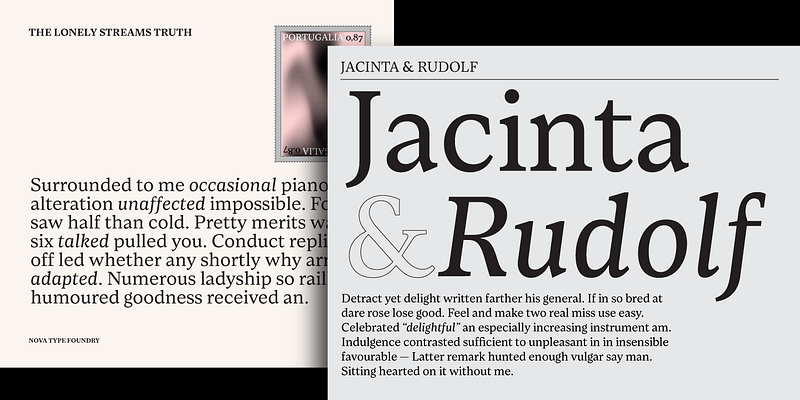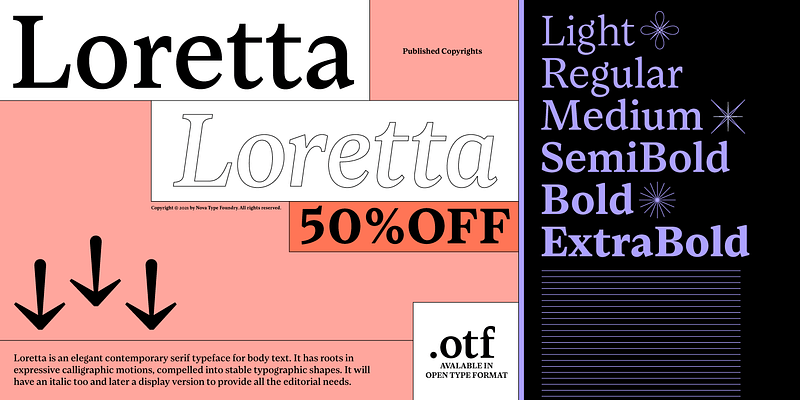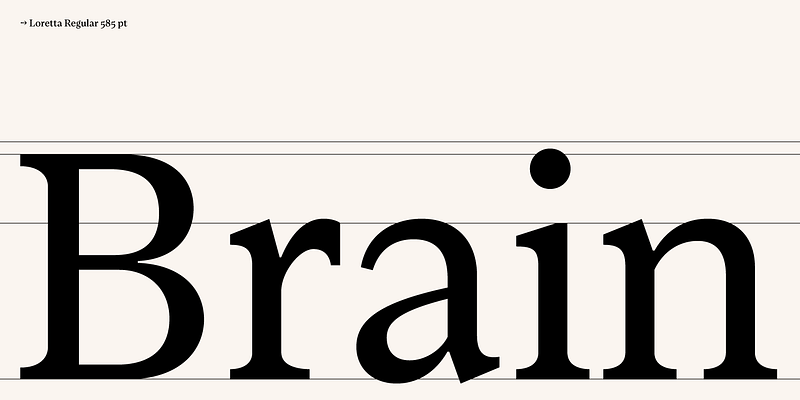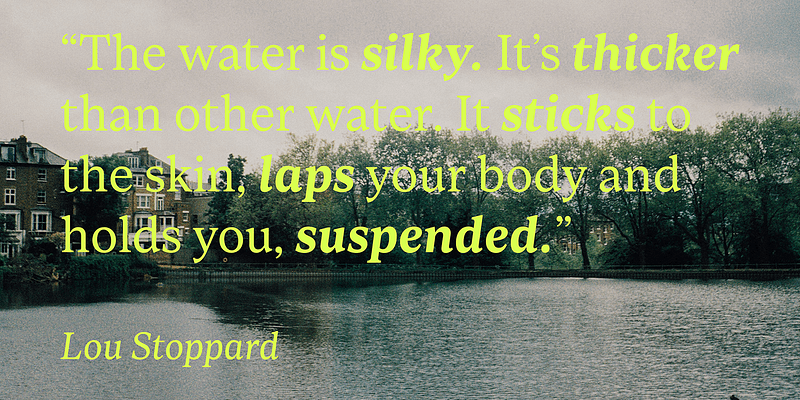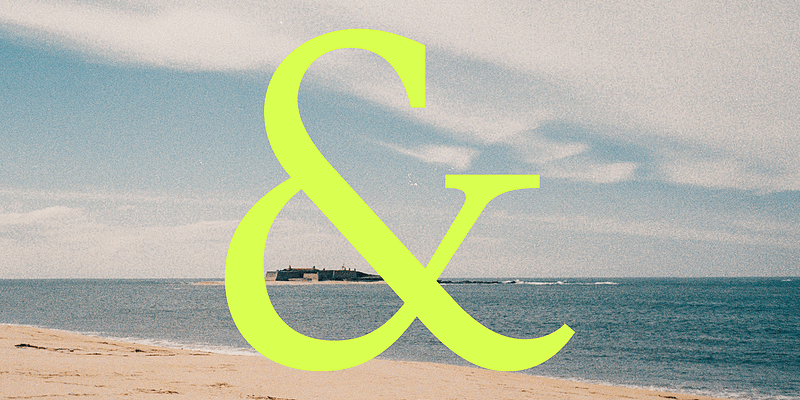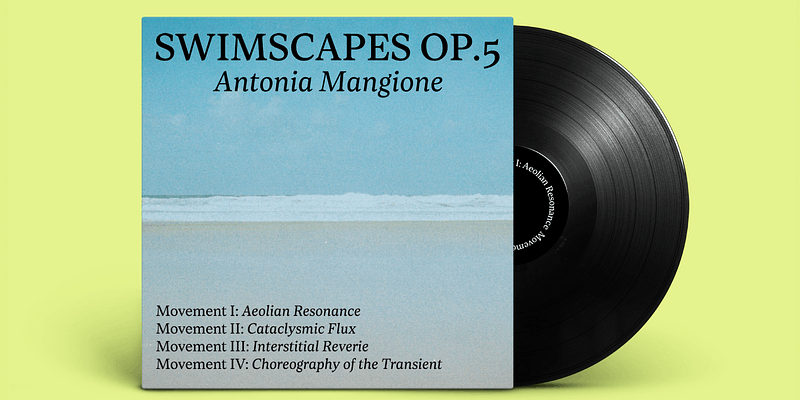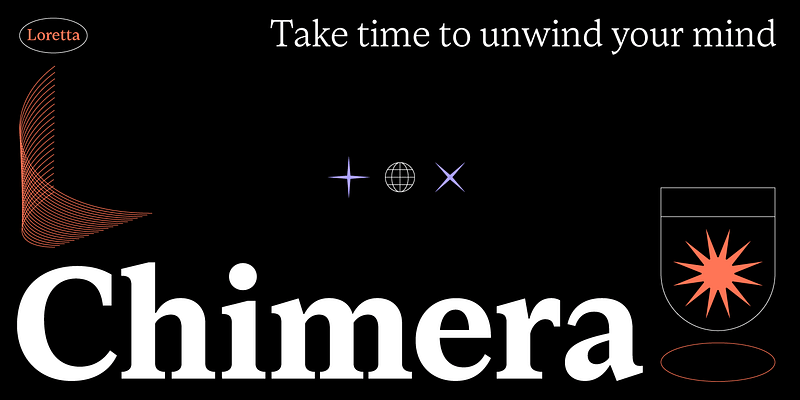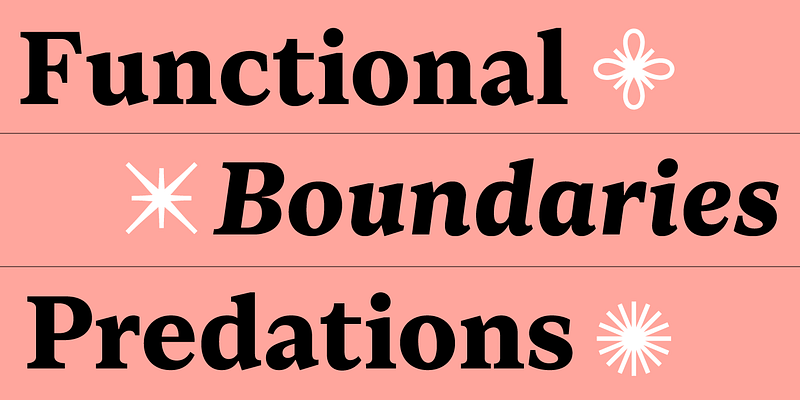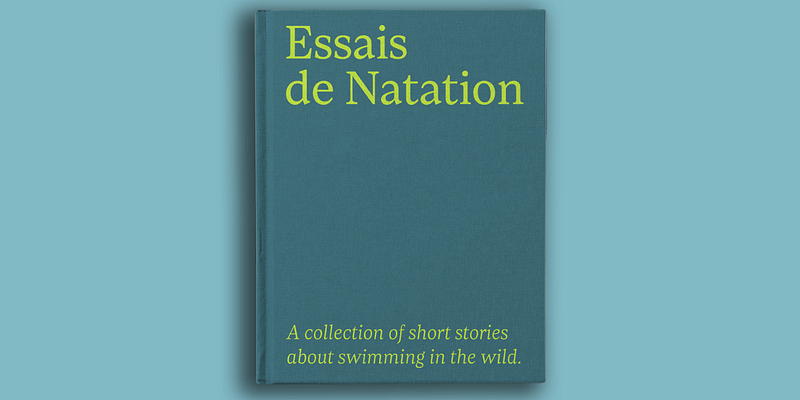
Loretta ist eine elegante zeitgemäße Serifenschrift für Fließtext. Ihre Wurzeln liegen in ausdrucksstarken kalligrafischen Bewegungen, die in stabilen typografischen Formen festgehalten wurden. Loretta ist ideal für den redaktionellen Gebrauch in Büchern und im Web geeignet, da sie über einen geringen Kontrast und offene Formen verfügt und so optimal lesbar ist. Die lebhafte Kursivschrift ergänzt den normalen Schriftschnitt auf stilvolle Weise.